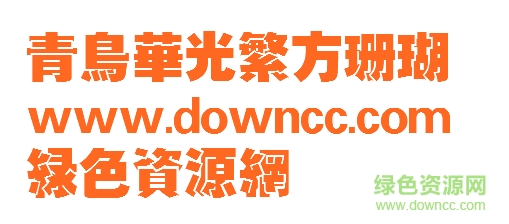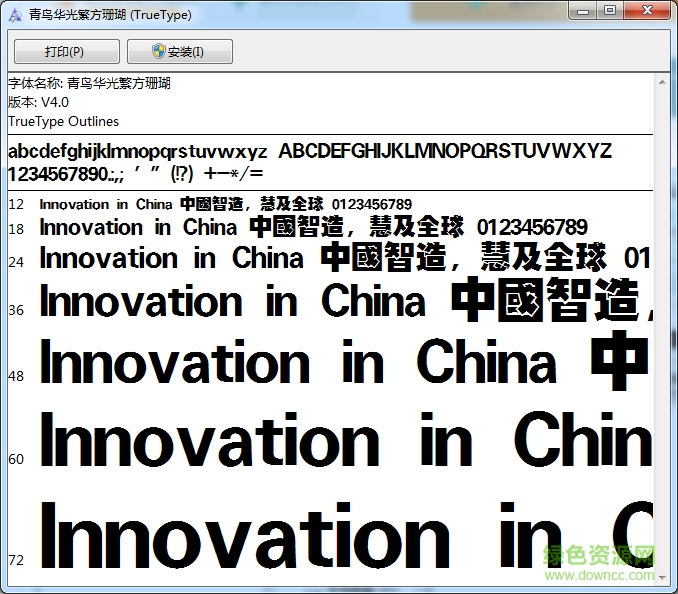
青鳥華光繁方珊瑚是青鳥華光字庫全新推出的珊瑚字體,支持簡體輸入自動轉(zhuǎn)化成繁體字,簡單大方的造型能贏得觀眾的視覺好感,喜歡的朋友快來綠色資源網(wǎng)體驗吧!
青鳥華光繁方珊瑚,繁體中文字體,造型粗黑段長,沿襲了黑體和宋體的藝術(shù)特色,整體顯得更加明亮和莊重,可廣泛運(yùn)用于平面設(shè)計、海報設(shè)計、排版印刷等諸多領(lǐng)域!
本站為大家提供方正細(xì)珊瑚、迷你簡細(xì)珊等珊瑚字體,而青鳥華光繁方珊瑚是一款粗珊瑚字體,整體設(shè)計粗黑大方,更方便識別和觀賞!